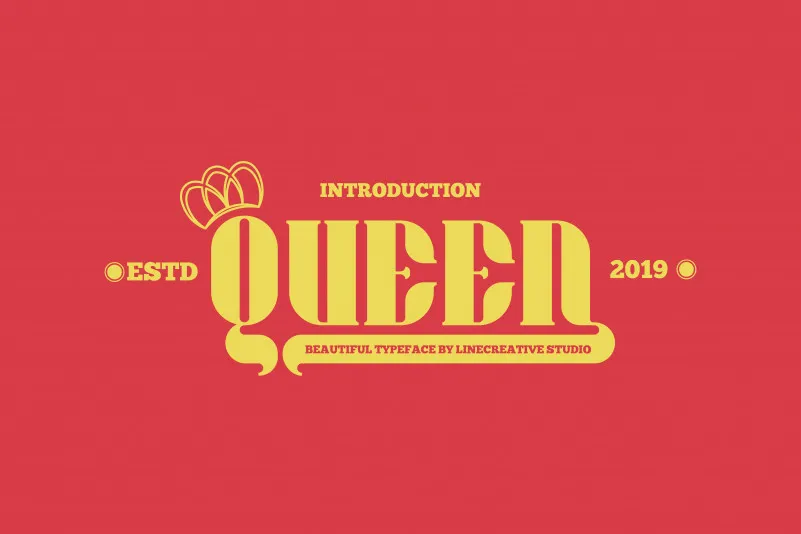
A Queen Font é uma escolha perfeita para apreciadores do design clássico que buscam unir o passado ao presente com modernidade. Inspirada no amor por histórias antigas e sua aplicação moderna, foi projetada para artistas apaixonados pelo passado. O conceito desta fonte permite usos tanto em escrita clássica quanto na era contemporânea, mantendo um toque vintage distintivo através de sua facilidade de leitura e suavidade. Se você é uma pessoa que aprecia o equilíbrio entre a história e as novas tendências, agora é o momento de expressar seu gosto por ambas as épocas com o Queen Display Font. Este design elegante e dinâmico oferece uma maneira única de unir os elementos do passado ao futuro, trazendo um toque vintage para a era moderna. Descubra o refinamento da arte que é a Queen Font.